モリサワは「写真植字」を発明して以来、一貫して「文字の未来」をみつめて研究・開発を続けてきました。
モリサワと聞いて「フォント」のメーカーだとイメージする方は多いと思います。「フォント」ひいては「文字」は、なにかしらのことばや情報を表すために用いる材料のひとつでしかなく、相手に伝えるためには「文字」を並べて組む「組版」が必須です。
文字は「組む」もの?「流す」もの?
活版印刷の時代
デザインや制作に関わる方であれば、文字を並べていくことを「文字を組む」「組版する」と表現するのを聞いたことがあるのではないでしょうか?
これは活版印刷の工程に由来していると言われています。
文字を組むためには、まず原稿に合わせて「活字棚」から活字を拾う必要がありました。この作業を「文選」と呼びます。
書体や文字サイズごとに活字が必要だったため、保管のためには広いスペースを要しました。
鉛の活字は重く、床が抜けないように補強工事が行われることもありました。
拾い集められた活字は「文選箱」に収められ、そこから原稿通りに並べていく「植字」が行われます。
そうして並べられた活字は、結束糸で縛られ「組み版」となります。
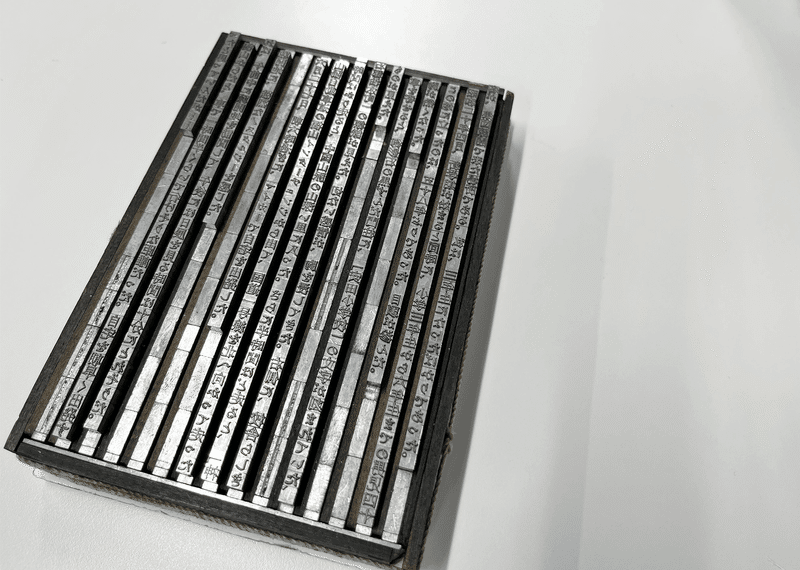
このように、文字を並べて版を組むことを「組版」と呼び、活字からフォントに変わった現在でも同じ言葉が使われています。
写真植字(写植)の時代
その後、「写真植字(写植)」という印刷技術が登場します。
原稿通りに文字を並べる「植字」を写真技術で行う方法で、活字のように広いスペースを必要としない写植は非常に画期的な技術でした。
モリサワの創業者である森澤信夫は、共同開発者の石井茂吉氏とともに、「邦文写真植字機」を世界で初めて発明しました。
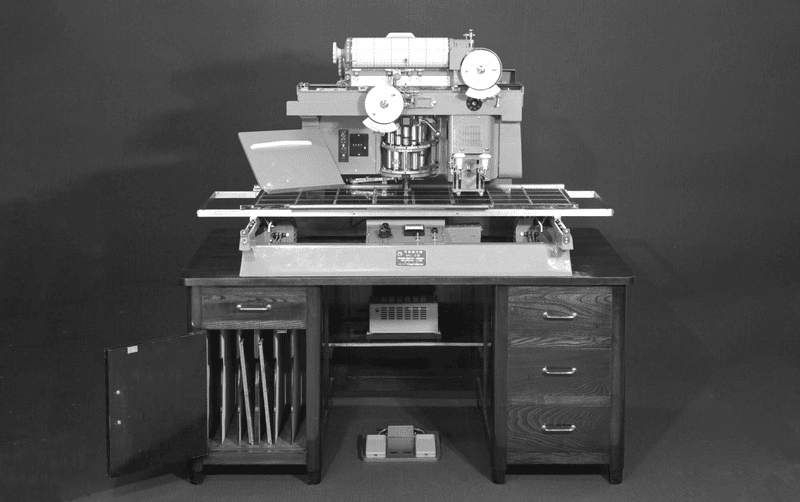
「写植」の機械はほとんど残っていませんが、その言葉だけは今でも現場で使用されることがあります。
特に漫画の原稿に文字を入れる作業を「写植」と呼ぶことが多いようです。
フォントとアプリケーションの時代
現在はパソコンとアプリケーションがあれば、誰でも文字を組むことができます。
活版印刷の時代のように、一つひとつ文字を手作業で並べていく必要はありません。アプリケーションで文字を入れるためのフレームを作成し、そこに原稿をコピー・ペーストすれば、文字を並べてくれます。
そのため、過去の職人が培ってきた組版の知識は意識されることが少なくなってきました。
しかし、アプリケーションにコピー・ペーストする、いわゆる「流す」だけでは思ったように文字が並んでくれないこともあります。また、どのように並べるのが最適なのか迷うこともあるでしょう。
読みやすく相手に伝わりやすいように文字を並べるためにも、ぜひ文字を「組む」こと、「組版」を意識してみてください。
「正しい組版」や「間違った組版」って存在するの?
さっそくですが、①の組版の例を見て、どのように感じますか?
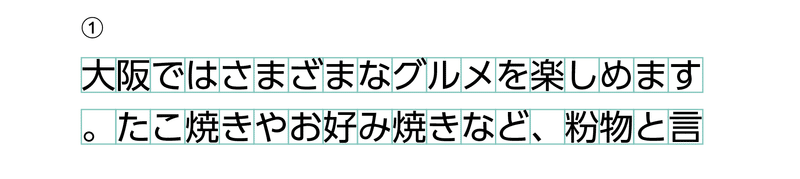
おそらく、多くの人が違和感を覚えると思います。いわゆる「組版ルール」を知っている・知らないに関わらず、NGとされる例です。
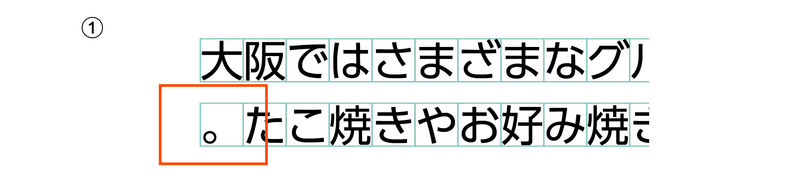
この例では行の先頭に句点がきています。
句点や読点などは行頭禁則文字と呼ばれ、「禁則処理」によって行の先頭には配置されないように処理します。学校で作文を書く際にも習うため、一般的にもよく知られているルールです。
それでは②はどうでしょう?
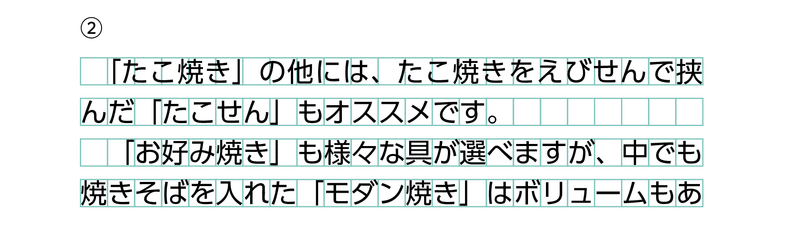
②は一見すると問題ありませんが、Aの箇所とBの箇所とで文字の並べ方が異なっています。
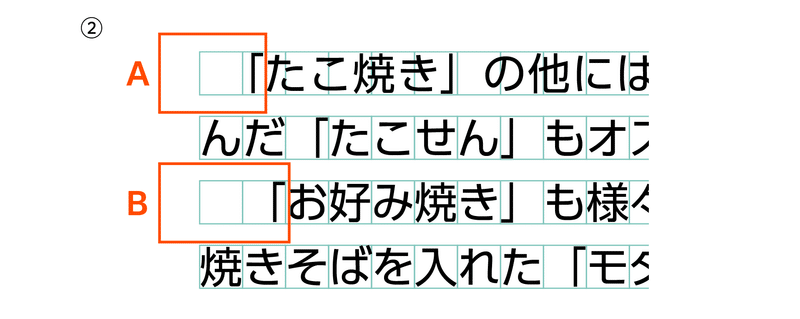
このように、組版には「守らなければいけないルール」と、媒体などの中で「統一したほうが良いルール」とが存在します。
また、「守らなければいけないルール」も、下記の③の場合のようにデザインを重視する(この場合は勢いを重視する、でしょうか)こともあります。
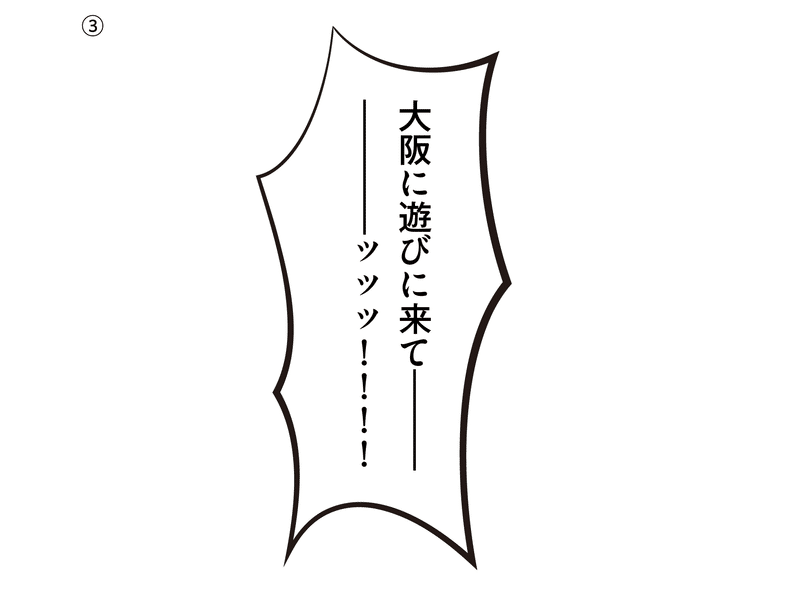
文字を組む際には、その文字が表す内容や、媒体(メディア)、見られる場所、見る人など、さまざまな状況や対象を考慮する必要があります。
今回の連載では、「日本語における書籍などの本文組み」を例にご紹介していきます。
基準となる組版ルール
組版には基準となるルールがあることをご存知でしょうか?
日本語の場合、「JIS X 4051」および、その実質的な後継ともいえる「日本語組版処理の要件(日本語版)/JLReq」がそれに当たります。
これらには、日本語組版に関する要件がまとめられています。
ちなみに英文組版の場合、
アメリカの「シカゴルール(The Chicago Manual of Style)」
イギリスの「オックスフォードルール(New Oxford Style Manual)」
があります。
英文組版をする場合は、手元にスタイルガイドの書籍を揃えておくと参考になります。
ただ内容は全て英語で書かれている上、とても分厚いため、すべて読むのは現実的ではありません。
前述のとおり、これらの組版ルールはすべての場合に適用されるとは限りません。時と場合によって柔軟にカスタマイズすることが必要です。
読んでいる相手に違和感を覚えさせず、書かれた内容をスムーズに伝えるためにも、ぜひ一緒に組版の基礎を学んでいきましょう!